폰트
PPT를 제작하거나 상품 홍보 디자인, 웹디자인 등을 할 때 폰트를 사용하게 됩니다. 그러나 상업적인 이용이 불가능한 폰트를 사용했을 경우 저작권 문제가 재기 되거나 폰트를 사용할 때 요금을 내고 사용해야 하는 경우가 종종 있어 곤란합니다. 웹디자인이나 편집 디자인을 하기 위해서는 글씨체가 보통보다 두껍고 모서리가 둥글둥글한 폰트를 사용해야 디자인은 물론 가독성도 높아지는데요, 오늘은 그런 분들을 위해 저작권 무료 폰트 총 8종에 대해 함께 알아보도록 하겠습니다.
1. 상상토끼 꽃길체
두꺼운 손글씨 느낌의 폰트로 자유롭고 거친 느낌이 있습니다. 사용 용도에 따라 고급스러운 느낌과 귀여운 느낌을 줄 수 있습니다. 꽃길체는 폰트 회사에서 무료로 제공하는 폰트로, 회원가입 후 무료로 사용이 가능합니다. 개인/기업/상업용 무료 폰트로, 폰트 자체를 판매하는 행위 및 파일 수정은 불가능합니다.
2. 빙그레 싸만코체
붕어싸만코 표지에 사용되는 폰트입니다. 부드럽고 귀여운 느낌을 주며, 둥글둥글해 가독성도 높습니다. 저작권은 개인/기업/상업용 모두 무료이며 빙그레 서체가 사용된 작업물은 빙그레 홍보에 사용할 수 있다는 전제가 있습니다.
3. 넥슨 배찌체
넥슨의 대표적인 게임 중 하나인 카트라이더 속 캐릭터 배찌를 모티브로 제작된 폰트입니다. 라인이 많이 두껍지도 얇지도 않고 일정하게 유지되어 가독성은 물론 손글씨의 느낌까지 주는 글씨체라 추천드립니다. 개인/기업/상업용 용도로 사용이 가능하며 폰트 자체 판매 및 파일 수정은 불가능합니다. 빙그레와 마찬가지로 해당 폰트가 사용 된 작업물은 자사 홍보를 위해 사용할 수 있습니다.
4. 엄마까투리체
안동시에서 지역 캐릭터를 홍보하기 위해 제작한 폰트로, 두껍고 옹골차며 귀여운 느낌을 주기 때문에 제목으로도 어울리는 폰트입니다. 개인/기업/상업용 모두 무료이며 특별한 허가 절차 없이 자유롭게 사용이 가능합니다.
5. 삼립호빵체
삼립에서 판매되는 호빵의 포장지 속 폰트로, 호빵 같은 느낌의 글씨체로 두꺼운 폰트와 속이 빈 폰트 두가지 종류가 있습니다. 영문 폰트도 호환이 가능해 편리합니다. 개인/상업적 용도로 사용이 가능하며 폰트 자체 판매 및 파일 수정은 불가하며 사용 시 출처를 표기해야 합니다.
6. 쿠키런 폰트
앞서 알려드린 엄마까투리체와 비슷하지만 조금 더 각지고 딱딱한 느낌으로, 제목으로도 어울리며 가독성이 높습니다. 개인/상업용 무료이며 폰트 자체 판매 및 파일 수정은 불가합니다. 추가로, 게임산업군에서는 PC 및 모바일 둘 다 개인/상업적 용도로 사용이 불가능합니다.
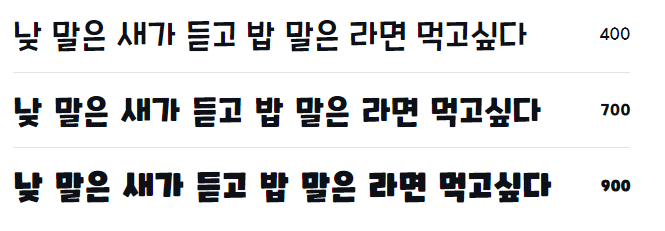
7. 망고빙수체
각이 딱딱 떨어지는 절제된 느낌과 라운딩 된 귀여운 느낌이 공존하는 폰트로, 영문 호환도 가능합니다. 영리 목적의 판매를 제외한 개인/기업 사용이 가능하며 2차 수정 및 배포가 가능합니다.
8. 레몬빙수
속이 비어있는 귀여운 폰트입니다. 라인이 상당히 두꺼워 글씨 하나하나가 마치 블록처럼 되어 있으며, 영문 호환이 가능해 귀여운 연출이 가능합니다. 개인/상업용으로 사용이 가능하며 영리 목적 판매 외에 수정 및 배포가 가능합니다.